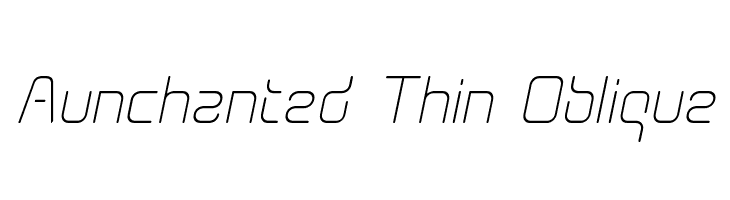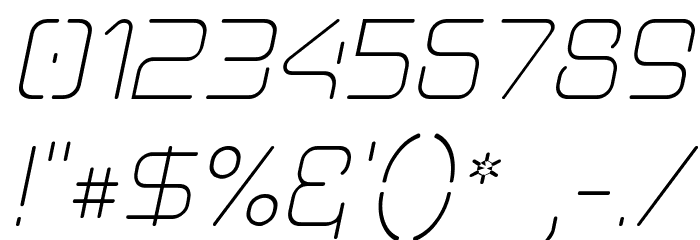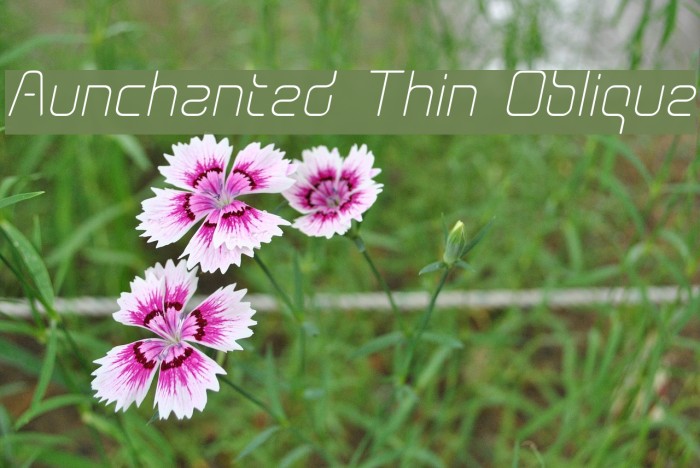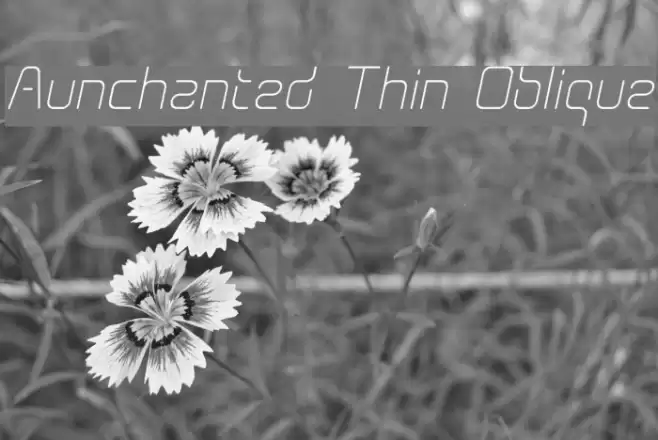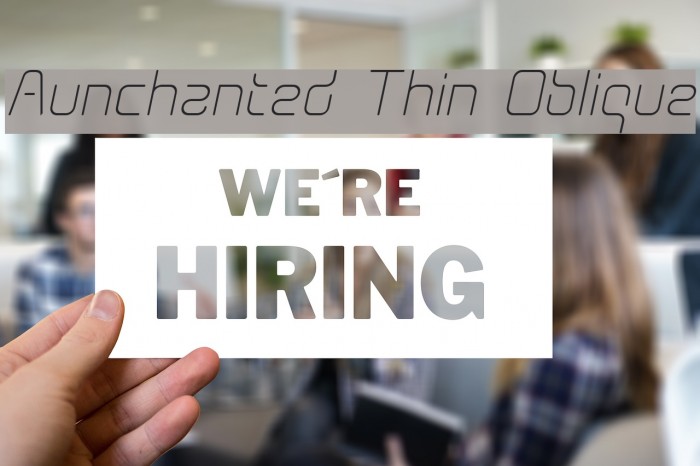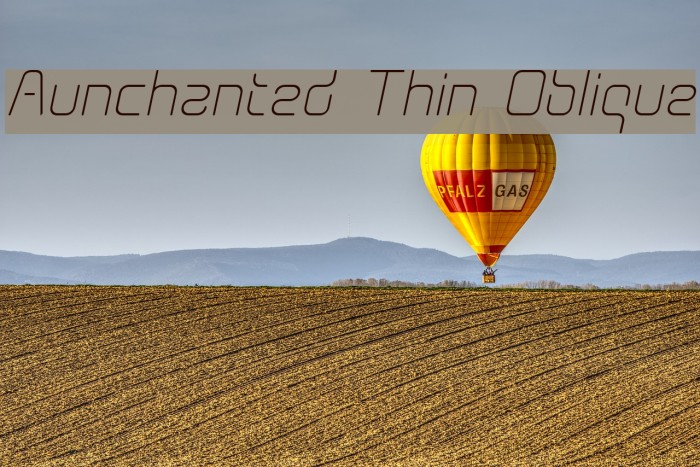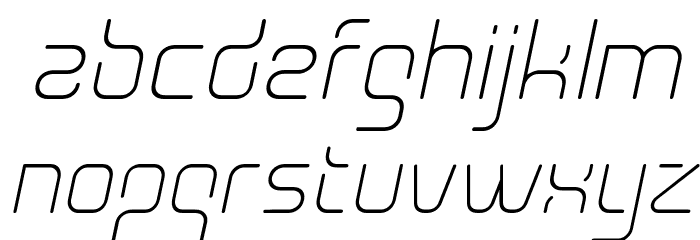
Aunchanted Thin Oblique Font
| Cas d'utilisation | Headlines, Logos, Digital Interfaces |
| Projets proposés | Ideal for tech branding, modern websites, digital interfaces, and futuristic-themed designs. |